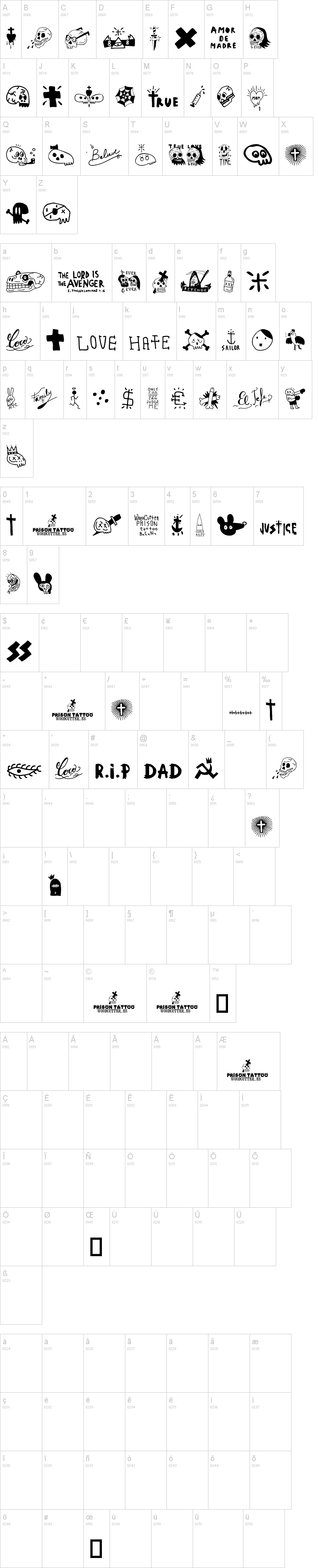
Woodcutter Prison Tattoo 是一种具有独特视觉风格的字体,其设计灵感来源于监狱纹身文化。这种字体呈现了一种粗犷、原始的感觉,字母形状较为扭曲、生硬,并带有一些刺针的效果,让人联想到囚犯在监狱里纹身的场景。 这种字体通常用于表现一些有冲击力、叛逆、反叛或者具有犯罪色彩的场景,例如电影海报、音乐专辑封面、游戏界面等。它比较适合用在较小的文本区域,以强调文字的重要性和视觉冲击力,也可以在其他艺术设计领域中发挥独特的效果。内容介绍
Woodcutter Prison Tattoo是一款非常不错的手写艺术字体,具有很好的视觉感,适合于文化类的宣传设计、商业类品牌的广告和产品包装设计以及个性化文字排版等较多场景。